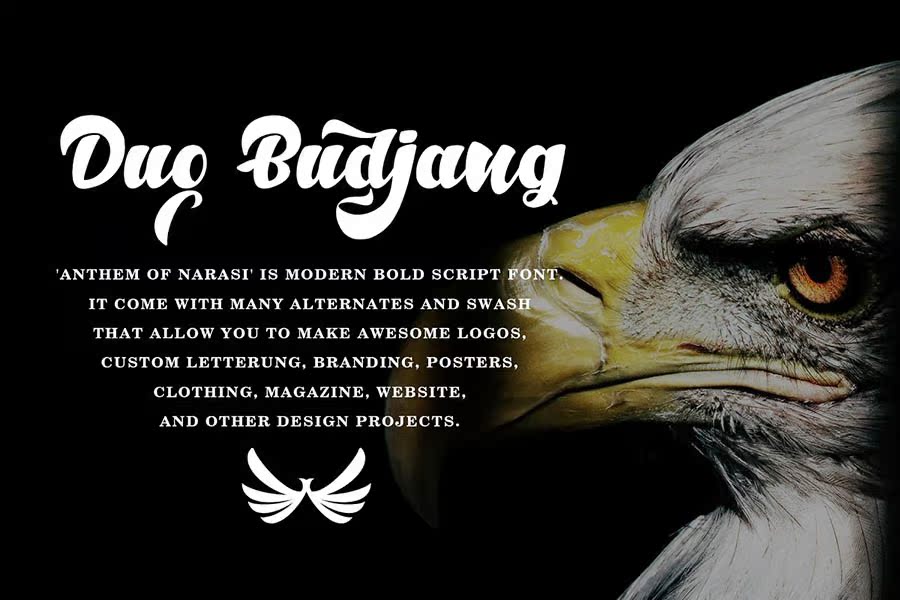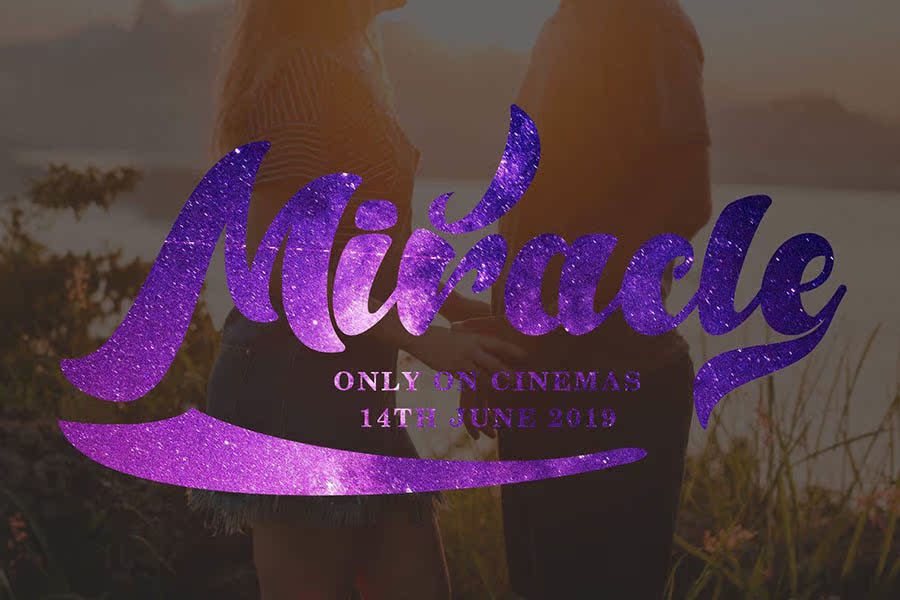
AnthemofNarasiFontDemofDemofNarasiFontDemofIsaStyleshandQuirkyNewBoldscript。AnthemofNarasiFontDemofNarsiShandNewBoldscript创建了一个尽可能,和Swash。这款香水是为那些想展示光滑和现代的东西的人而设计的。如果你想吸引现代买家,你可以使用这款香水。这款香水的外观设计似乎表明你在业务上具有专业能力,并热爱你向客户提供的产品和服务。